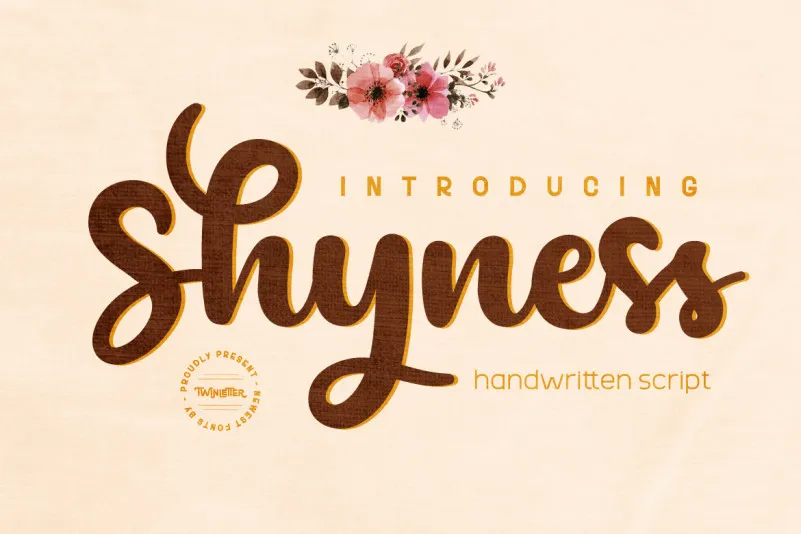
Shyness Font – Fonte Grátis
Shyness Font
Esta é uma fonte script escrita a mão com um background clássico e autêntico em várias elegantes estilos. As letras foram criadas usando diversas referências para criar uma impressão forte e aguda, garantindo que o seu mensageiro seja transmitido de maneira impactante a todos os ouvintes. A fonte Shyness é perfeitamente adaptada para trabalhos onde deseja expressar com simplicidade e elegância ao mesmo tempo. Se você está procurando por uma fonte script escrita a mão, que transmite autoridade sem parecer chique demais, pode encontrar isso na Shyness Font de twinletter.